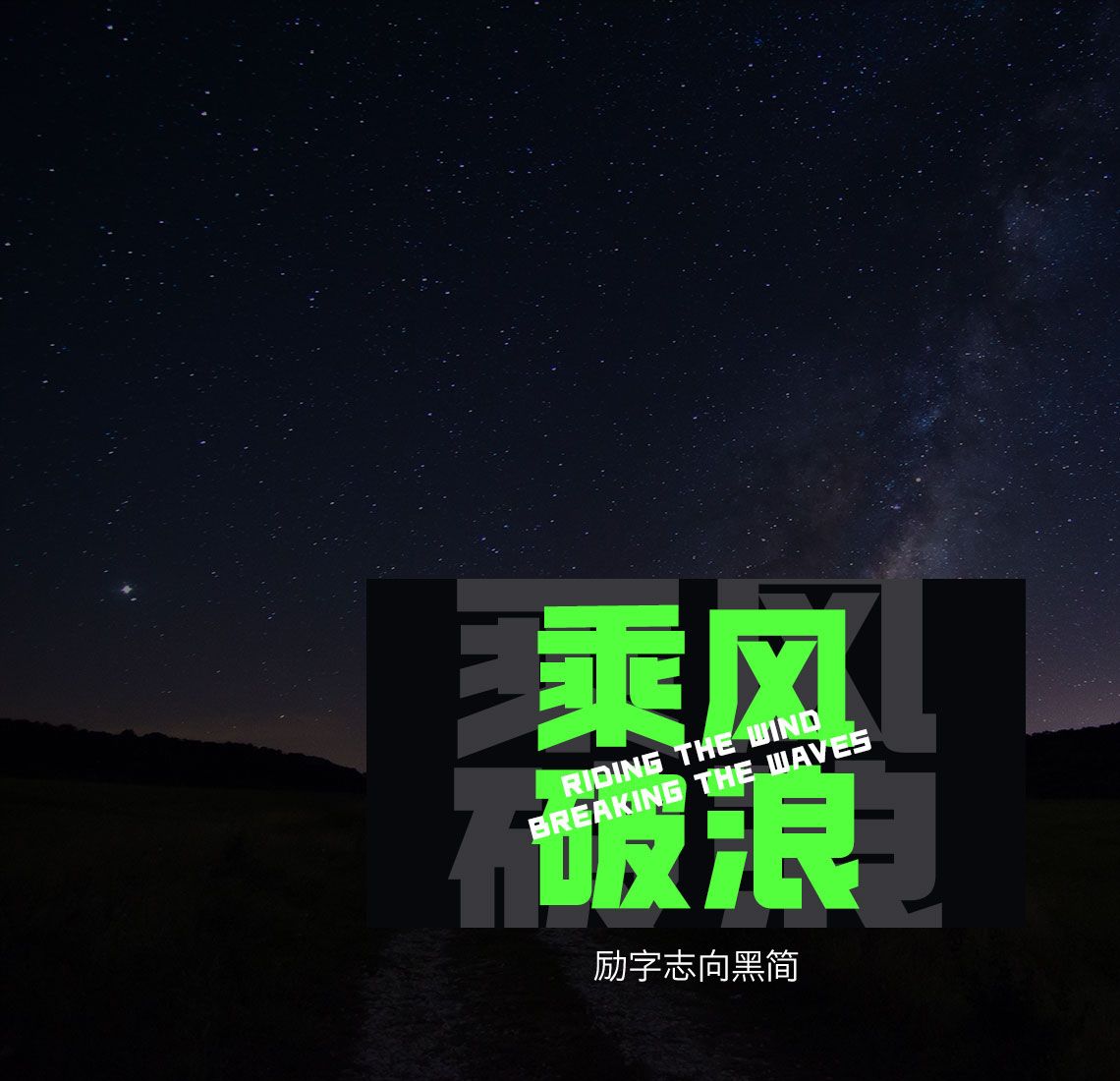
首款高考应用字体——励字志向黑简,闪耀着梦想的光芒
6月7日,
6月8日,
6月9日,
一帮未满18岁的孩子,走上战场,
迎来一场场最平静的战争。
高考的过来人说,
“再长的路,一步一步也能走完,再短的路,不迈开双脚也无法到达”
还有无用的秘诀,
“高考得高分的秘诀就是少丢分”;
还有励字造梦字库推出首款高考应用字体——励字志向黑简
每一分拼搏,都闪耀着梦想的光芒,
每一笔墨痕,都书写着未来的辉煌。
励字志向黑简,采用圆体与黑体的融合,在笔画拐角增加适当的外圆角的手法在整体稳重大气的字形中增添少许灵动,使字体字面充实,结构稳定之余,更适配屏显的使用。